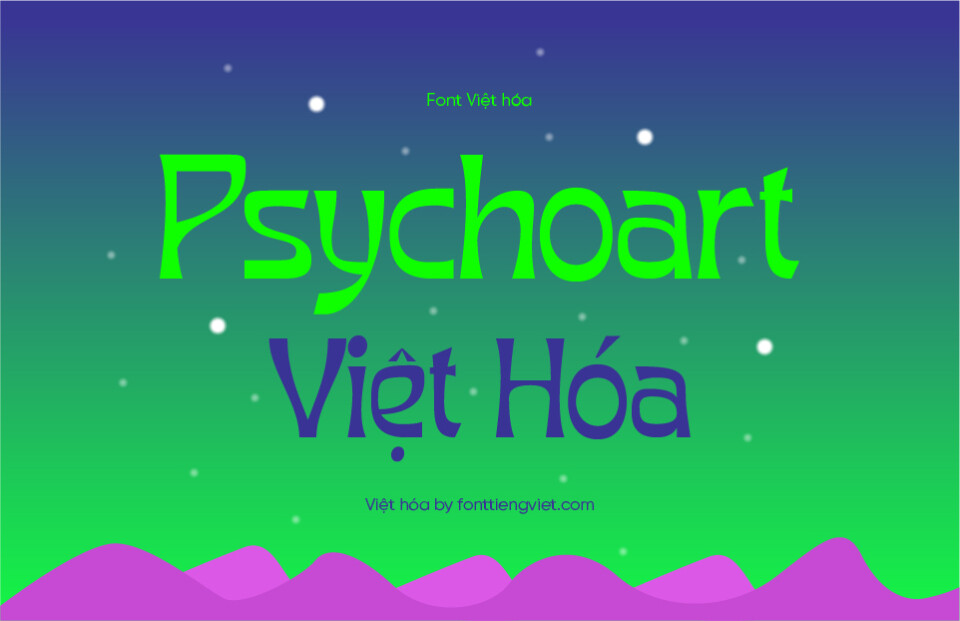
Font Việt hóa 1FTV Psychoart
Giới thiệu về Font Việt hóa 1FTV Psychoart
Trong thế giới thiết kế đồ họa hiện đại, việc lựa chọn một bộ Font Miễn Phí chất lượng là yếu tố quyết định sự thành công của một tác phẩm. Font Việt hóa 1FTV Psychoart nổi lên như một hiện tượng nhờ phong cách nghệ thuật độc đáo, kết hợp giữa nét vẽ tay phóng khoáng và cấu trúc hình khối phá cách. Đây là lựa chọn hoàn hảo cho những bạn học sinh, sinh viên muốn tạo nên những bài thuyết trình ấn tượng hoặc các dự án sáng tạo cá nhân tại trường học.
Đặc điểm nổi bật của bộ font chữ
Điểm mạnh nhất của Font Việt hóa 1FTV Psychoart chính là sự linh hoạt trong ứng dụng. Bộ font này không chỉ giữ nguyên tinh thần nghệ thuật của phiên bản gốc mà còn được tối ưu hóa bảng mã tiếng Việt một cách tỉ mỉ. Các dấu thanh được tinh chỉnh khéo léo, giúp văn bản không bị lỗi hiển thị khi soạn thảo trên các phần mềm phổ biến như Photoshop, Canva hay Microsoft Word. Với đường nét đậm chất “Psychoart”, nó mang lại cảm giác mạnh mẽ, cá tính nhưng vẫn đảm bảo sự dễ đọc cần thiết.
Cách ứng dụng Font Việt hóa 1FTV Psychoart trong học tập và thiết kế
Các bạn có thể sử dụng bộ font này để thiết kế bìa báo tường, banner sự kiện trường học hoặc làm nổi bật các tiêu đề quan trọng trong bài tiểu luận. Nhờ tính nghệ thuật cao, nó giúp thu hút ánh nhìn ngay từ giây phút đầu tiên. Việc cài đặt cũng vô cùng đơn giản, giúp người dùng tiết kiệm thời gian tối đa để tập trung vào việc sáng tạo nội dung.